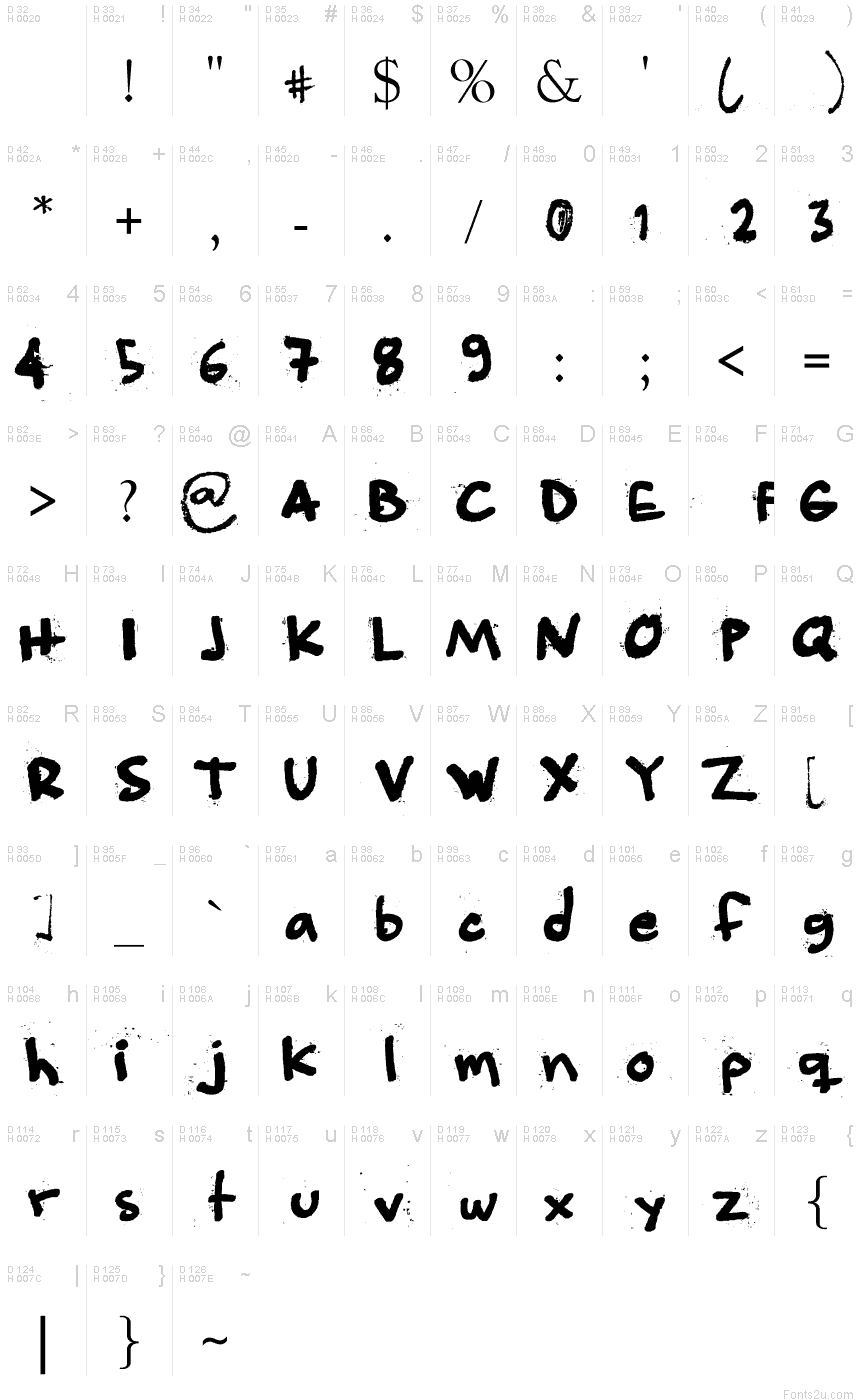
Angeleobardo to darmowy, surowy krój pism pędzlowych z grubymi, ręcznie malowanymi literami i wyrazistym pociągnięciem przypominającym marker. Nierówne krawędzie, plamy atramentu i nieregularne kształty nadają pismu surowe, zaimprowizowane wykończenie.
Jego ziarnista konstrukcja dobrze sprawdza się na plakatach muzycznych, okładkach albumów, gadżetach skate i opakowaniach streetwearu, które wymagają surowego, ręcznie robionego znaku. Zachowaj wokół oszczędne elementy, aby plamy i nieregularne kształty liter pozostały łatwe do odróżnienia.